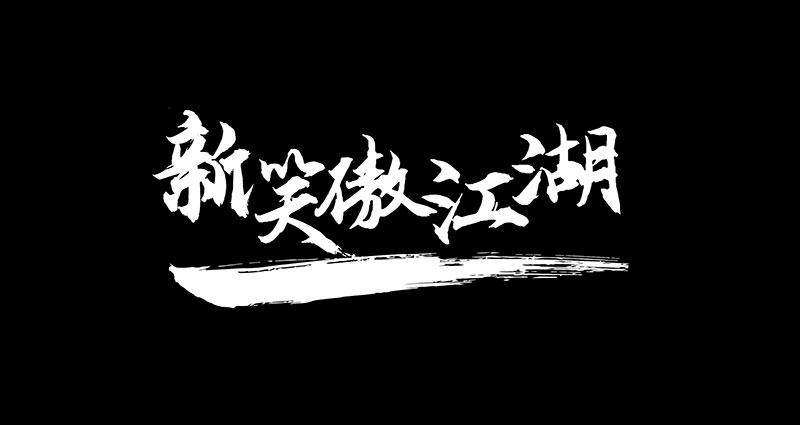
云峰飞云体
具有浓浓的毛笔风格,大气、豪放,可广泛用于平面设计、影视、海报等行业
字体介绍
继首款免费商用字体“云峰静龙行书 “之后,第二款免费商用字体云峰飞云体来了,本字体具有浓浓的毛笔风格,大气、豪放,可广泛用于平面设计、影视、海报等行业。法律范围内不限使用范围,禁止二次修改字体,禁止二次售卖字体。
字体应用示例